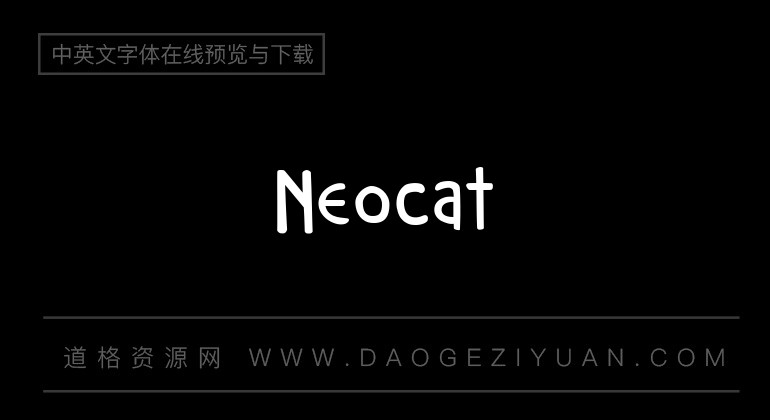
Neocat 字体是一款现代欧洲风格的字体,它具有清晰的结构和极具特色的笔画,适合用于标题、标签、标识等场景。它的特点是结构紧凑,字形清晰,笔画极具特色,而且可以很好地与其他字体搭配使用。Neocat 字体适用于各种设计项目,具有非常好的可读性和可视性,可以满足多种不同的设计需求。内容介绍
Neocat是一款非常不错的手写艺术字体,具有很好的视觉感,适合于文化类的宣传设计、商业类品牌的广告和产品包装设计以及个性化文字排版等较多场景。